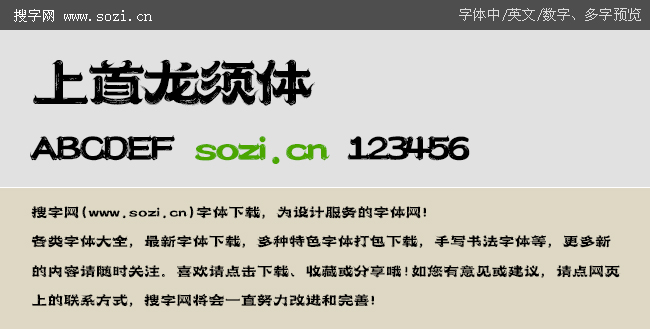
上首龍須體
搜字網(wǎng)給大家提供一款上首龍須體中文字體下載,上首龍須體筆畫均勻協(xié)調(diào)、順暢有力,收筆處細(xì)絲纖細(xì)而有力。字體中的筆畫和部首之間的連接自然流暢,整體呈現(xiàn)出一種傳統(tǒng)書法的韻味。適用于搭配標(biāo)志、廣告標(biāo)語、商業(yè)廣告等廣告設(shè)計(jì)。